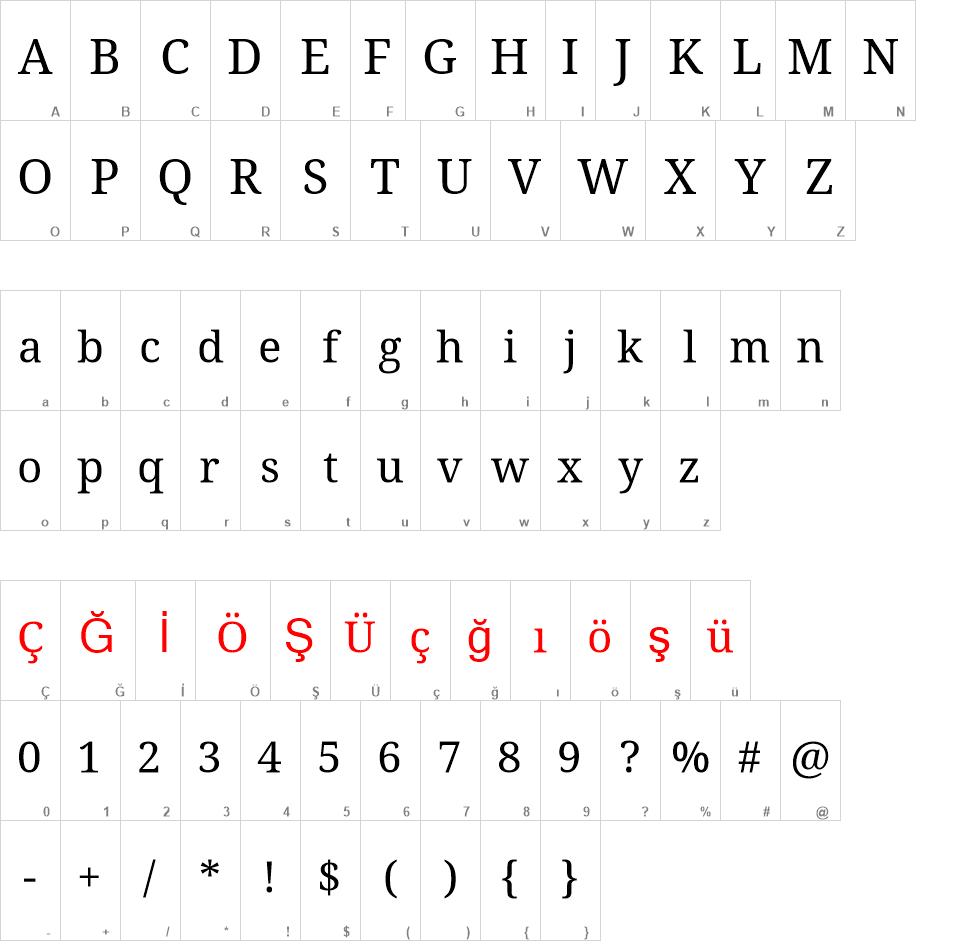
Droid Serif Font Family
Droid Serif ist eine moderne serif-Schriftfamilie, die für ein bequemes Lesen auf dem Bildschirm entwickelt wurde. Droid Serif ist etwas intensiviert, um die auf kleinen Bildschirmen angezeigte Textmenge zu maximieren. Vertikale Belastung und offene Formen tragen zur Lesbarkeit bei, während Proportionen und Gesamtdesign die begleitenden Droid Sans ergänzen.